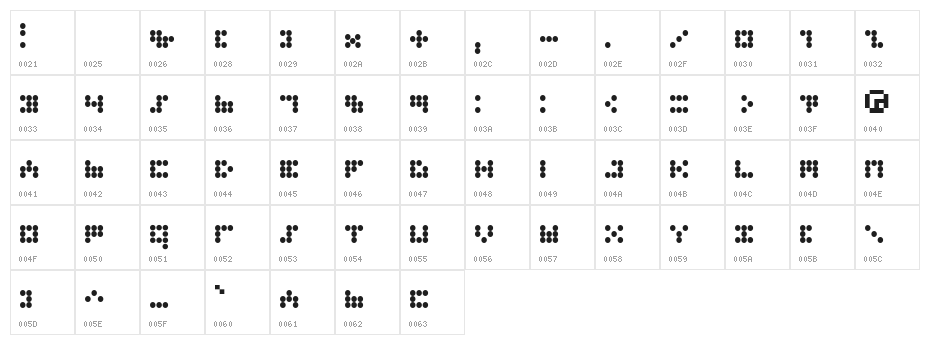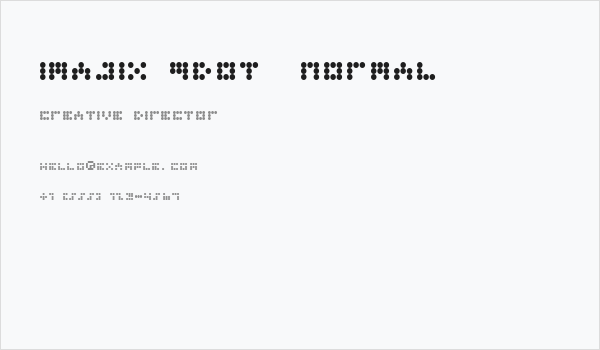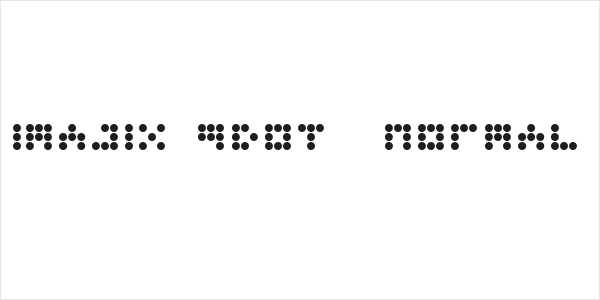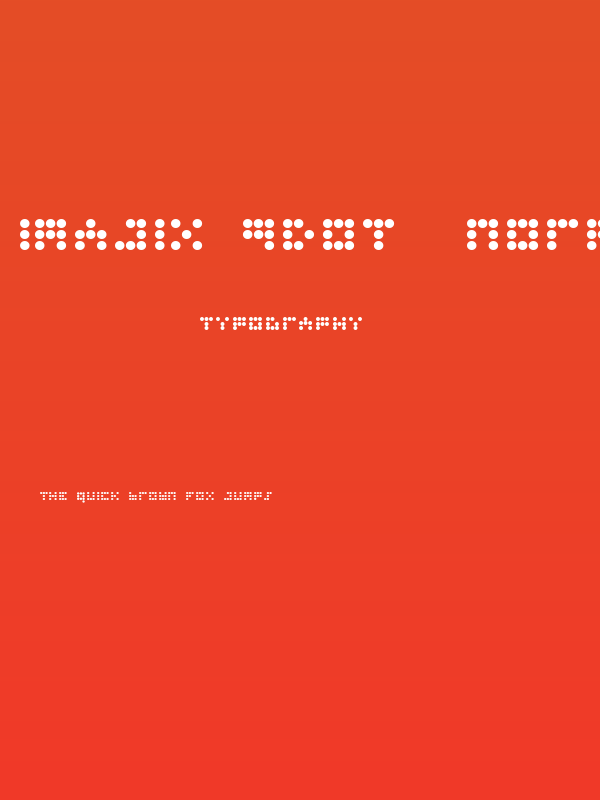
imajix 9dot Normal Font
| Anwendungsfall | Headlines, Logos, Digital interfaces |
| Vorgeschlagene Projekte | Ideal for digital displays, tech-themed designs, video game interfaces, and futuristic branding. |